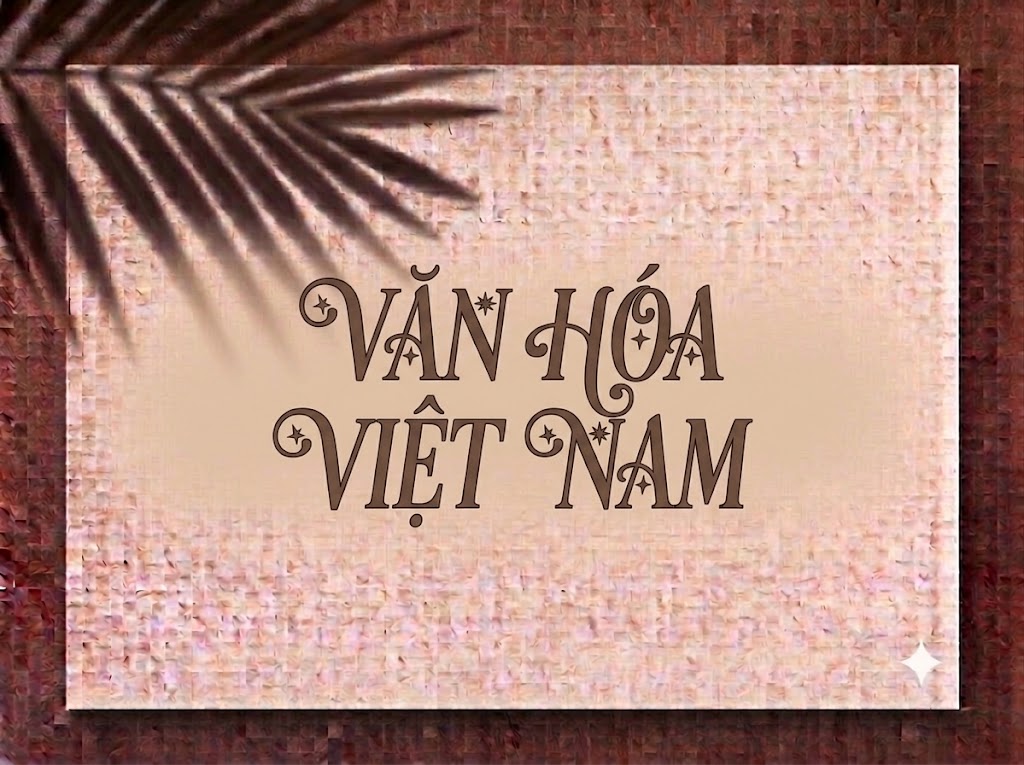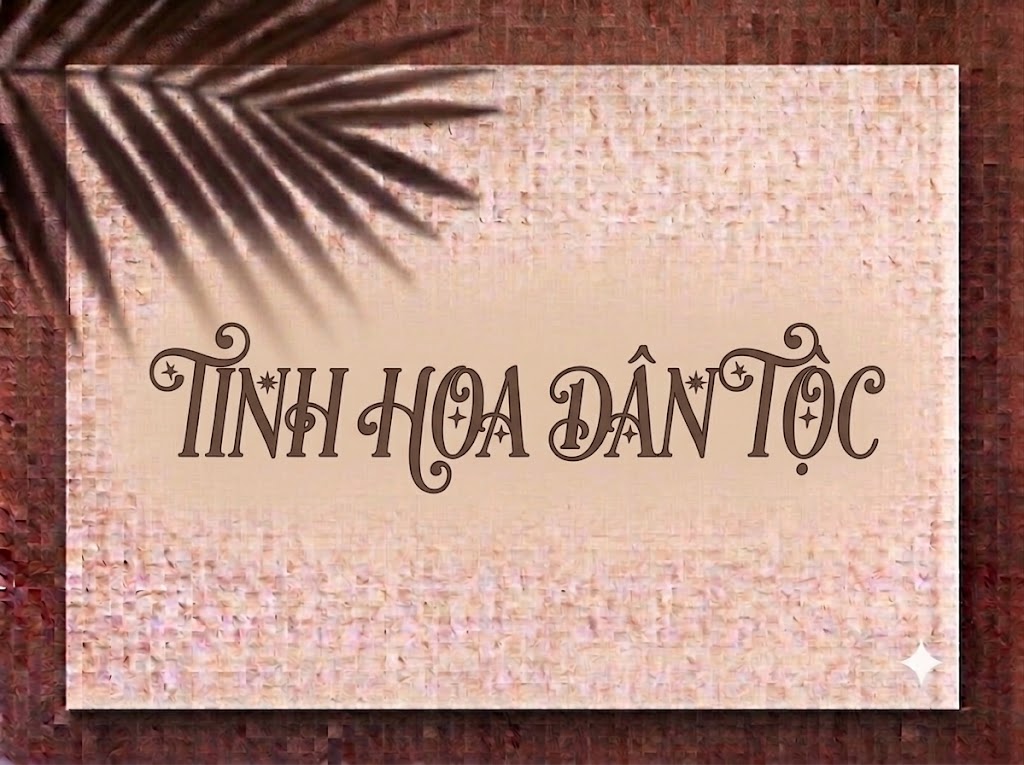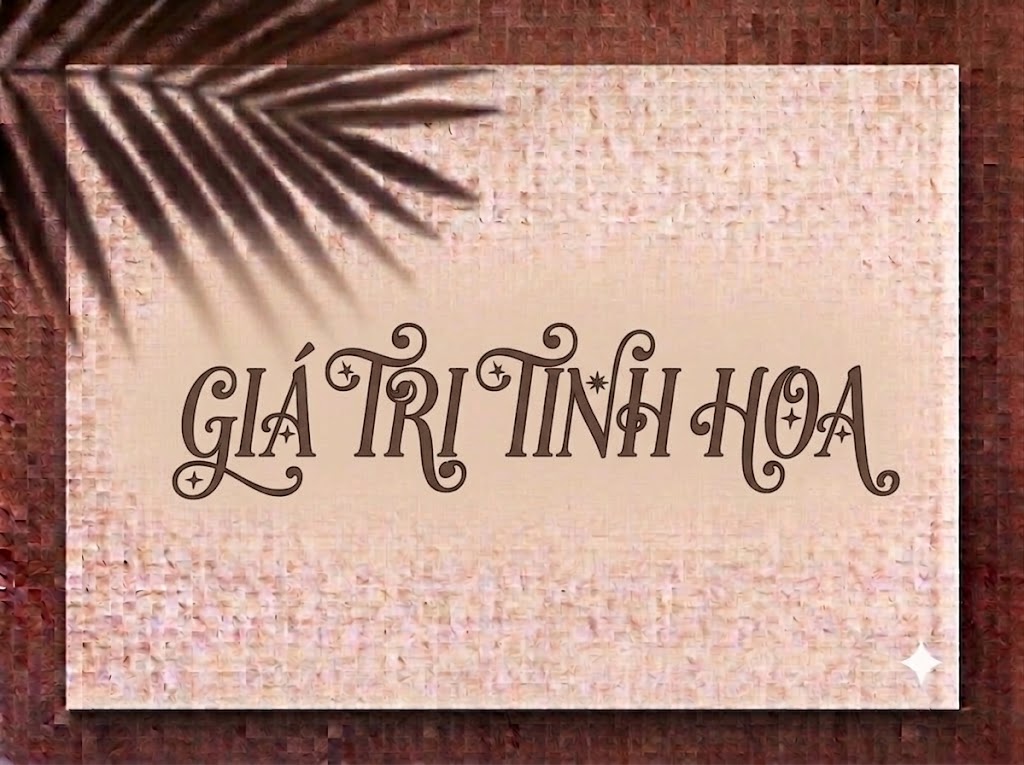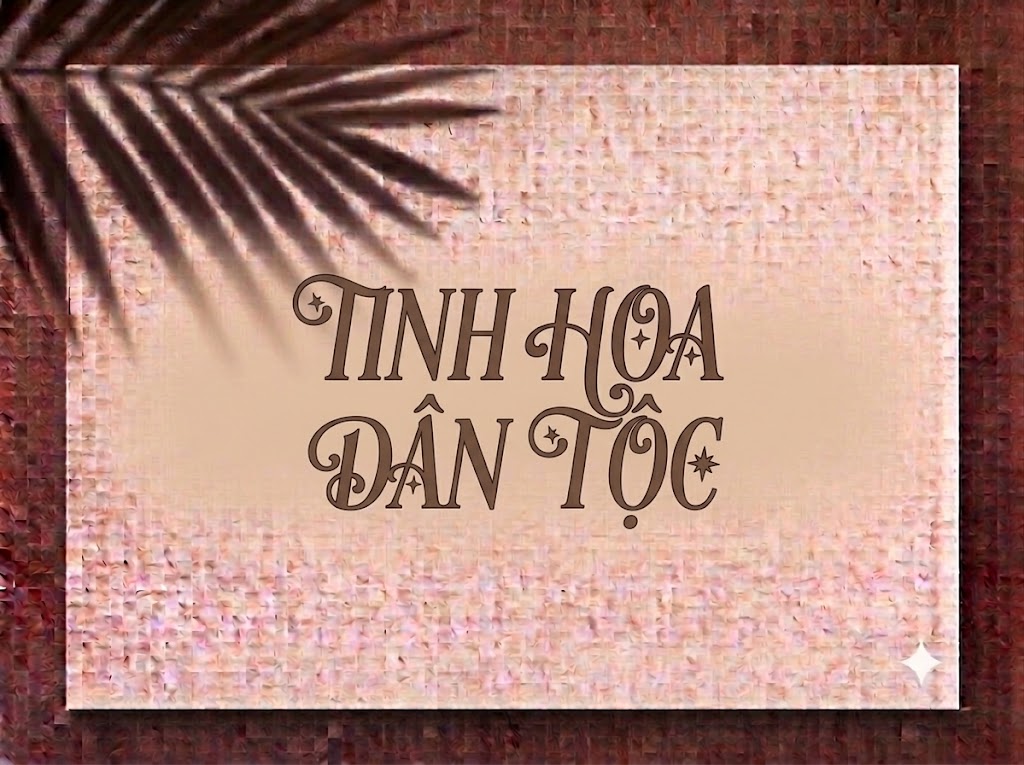
1FTV VIP Christmas Sundaylab
Mỗi mùa lễ hội Giáng sinh và Năm mới đến, các sản phẩm thiết kế truyền thông luôn cần những phông chữ mang đậm không khí ấm áp, kỳ diệu và tràn đầy niềm vui. Một dòng tiêu đề trang trí với những đường uốn xoắn ngộ nghĩnh không chỉ truyền tải thông điệp mùa lễ mà còn ngay lập tức thu hút thị giác, tạo cảm giác thân thiện và ngọt ngào cho ấn phẩm.
Nếu bạn đang tìm kiếm một phông chữ hiển thị trang trí chủ đề Noel cho banner quảng cáo sale, thiệp chúc mừng, menu quán café hay tiêu đề video ngắn mùa lễ hội, font 1FTV VIP Christmas Sundaylab chính là lựa chọn không thể bỏ qua.
Giới thiệu về font 1FTV VIP Christmas Sundaylab
Font 1FTV VIP Christmas Sundaylab là bộ chữ hiển thị trang trí (decorative display font) mang phong cách lễ hội cổ tích, nổi bật với cấu trúc chữ vui nhộn cùng các nét uốn lượn biến điệu cực kỳ độc đáo:
Tên phông chữ: 1FTV VIP Christmas Sundaylab
Phiên bản: Version 1.000
Thông số kỹ thuật: Định dạng OpenType Layout, tích hợp chữ ký kỹ thuật số (Digitally Signed) và hệ thống đường nét PostScript Outlines sắc nét.
Được hoàn thiện chỉn chu về mặt kỹ thuật, phông chữ đem lại khả năng hiển thị mượt mà trên mọi độ phân giải. Bạn có thể tự tin phóng lớn chữ trên các ứng dụng đồ họa chuyên nghiệp hay phần mềm dựng phim mà không lo gặp tình trạng vỡ nét hay răng cưa.
Đặc điểm nổi bật của phong cách thiết kế VIP Christmas Sundaylab
Sức hút thị giác của font 1FTV VIP Christmas Sundaylab đến từ sự kết hợp tài tình giữa nét chữ hoạt họa và chi tiết trang trí lễ hội:
Chi tiết uốn xoắn curlicue ngọt ngào: Điểm nhấn đáng yêu nhất của phông chữ nằm ở phần đầu và đuôi ký tự được nhấn nhá bằng các vòng cuộn xoắn mềm mại (như ở chữ Q, C, K, B, R, O, F, J, P, S), gợi liên tưởng đến những chiếc kẹo que hay ruy-băng trang trí Cây Thông Noel.
Phom dáng nhảy nhót sinh động: Độ cao và nét vẽ giữa các chữ cái được tạo hình biến điệu tự nhiên, mang lại cảm giác vui nhộn, hào hứng đúng tinh thần của những ngày lễ Giáng sinh.
Đồng bộ chữ hoa và chữ số: Hệ thống chữ cái in hoa và dãy số từ 0-9 đều được tạo hình theo chuẩn phong cách trang trí lễ hội, giúp các dòng tiêu đề chương trình hay ngày tháng Giáng sinh luôn nổi bật.
Để phông chữ vận hành mượt mà trên cả hệ điều hành Windows lẫn macOS, phiên bản này đã được tinh chỉnh kỹ lưỡng về thông số nội tại:
Khoảng cách giữa các chữ (kerning) và độ giãn dòng được tính toán chuẩn xác, giúp các nét uốn xoắn khi đứng cạnh nhau không bị dính nét hay rối mắt.
Tích hợp trọn vẹn bộ chữ cái, dãy chữ số 0-9 phom dáng sinh động cùng hệ thống ký tự đặc biệt, dấu câu thông dụng.
Bản Việt hóa chuẩn chỉnh giúp bạn hoàn toàn yên tâm thiết kế các văn bản tiếng Việt có dấu mà không gặp lỗi nhảy font hay mất ký tự.
Hình ảnh demo thực tế của font 1FTV VIP Christmas Sundaylab
Khả năng hiển thị của phông chữ này được tối ưu rất tốt trên nhiều tỷ lệ kích thước khác nhau:
Kích thước nhỏ (12pt – 24pt): Cấu trúc chữ rành mạch giúp các dòng chữ nhỏ vẫn hiển thị rõ ràng trên màn hình di động.
Kích thước lớn (36pt – 72pt): Đây là đất diễn lý tưởng nhất để 1FTV VIP Christmas Sundaylab phô diễn toàn bộ sự nhí nhảnh, ngọt ngào của các nét xoắn trang trí, tạo tác động thị giác mạnh mẽ cho các dòng headline chính.
Ứng dụng trong thiết kế đồ họa và làm video
Sở hữu nét cá tính lễ hội ấm áp và nổi bật, font 1FTV VIP Christmas Sundaylab mở ra không gian ứng dụng vô cùng rộng lớn:
Video ngắn (TikTok, Reels, Shorts): Dáng chữ trang trí ngộ nghĩnh này hiển thị rất thu hút trên khung hình đứng tỷ lệ 9:16. Cực kỳ ăn nhập với các video vlog chuẩn bị Noel, hướng dẫn làm bánh, trang trí nhà cửa hay ý tưởng quà tặng Giáng sinh.
Banner chương trình Flash Sale & E-commerce: Lựa chọn hàng đầu để giật tít các chiến dịch khuyến mãi “Christmas Sale”, “Happy New Year” trên Shopee, Lazada, TikTok Shop hay Facebook Banner.
Thiết kế Thiệp chúc mừng và Bao bì sản phẩm: Hoàn hảo cho các mẫu thiệp mừng Giáng sinh, nhãn mác hộp quà, bao bì bánh ngọt, cốc café mùa đông hoặc menu tiệc Giáng sinh.
Ảnh thu nhỏ YouTube (Thumbnail): Vũ khí tuyệt vời cho các kênh làm nội dung âm nhạc Noel, vlog đời sống, ẩm thực nhờ giao diện tươi vui và dễ thương.